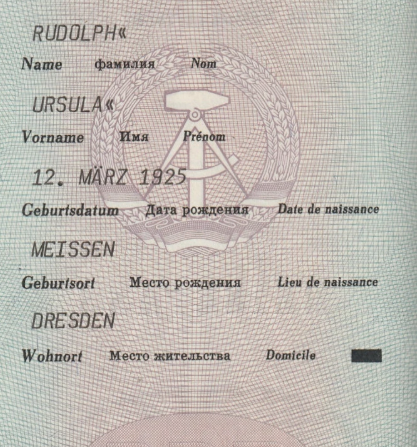
welche Schriftart für DDR Pässen?
Weiß jemand, welche Schriftart für die Eingabe der persönlichen Daten in den Pässen der DDR gegen Ende ihrer Existenz verwendet wurde?
Ich vermute, dass es sich um eine elektrische Schreibmaschine handelt – die Schrift sieht moderner aus als die typischen Schriftarten herkömmlicher Schreibmaschinen.
Unten findet ihr einige Fotos mit Beispielen.